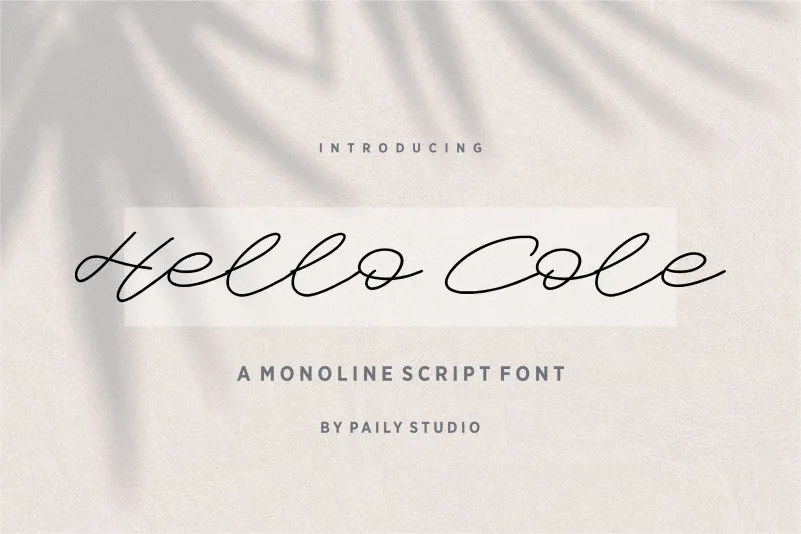
Hello Cole Font – Fonte Grátis
Hello Cole Font
A fonte “Hello Cole” é uma escolha perfeita para os designers que buscam uma tipografia elegante e versátil para seu trabalho criativo. Esta font é projetada para se adaptar a uma ampla gama de aplicativos, incluindo projetos de casamento, criação de marcas, logotipos, cartazes, cards de visita, convites, postagens em mídias sociais e muito mais. Com seu design suave e arredondado, “Hello Cole” adiciona um toque de elegância a qualquer projeto. Suas linhas leves e sua disposição cuidadosamente planejada permitem que seus projetos se destaquem sem ser exageradas ou difícil de ler. Seja em uma sessão de design de casamento sofisticada, uma campanha publicitária criativa ou até mesmo em um post emocionante no Instagram, a “Hello Cole” pode complementar seu trabalho e fazer dele ainda mais especial. Ideal tanto para designers profissionais quanto para pessoas que desejam adicionar um toque único a seus projetos pessoais, esta font é uma escolha confiável. A “Hello Cole Font” é perfeita para quem busca uma fonte elegante e versátil para criar design de alta qualidade, oferecendo uma opção única e sofisticada em sua paleta de ferramentas gráficas.
Designer: Paily Studio